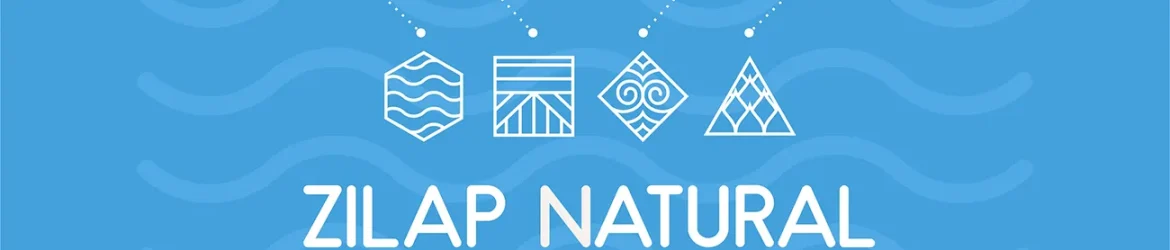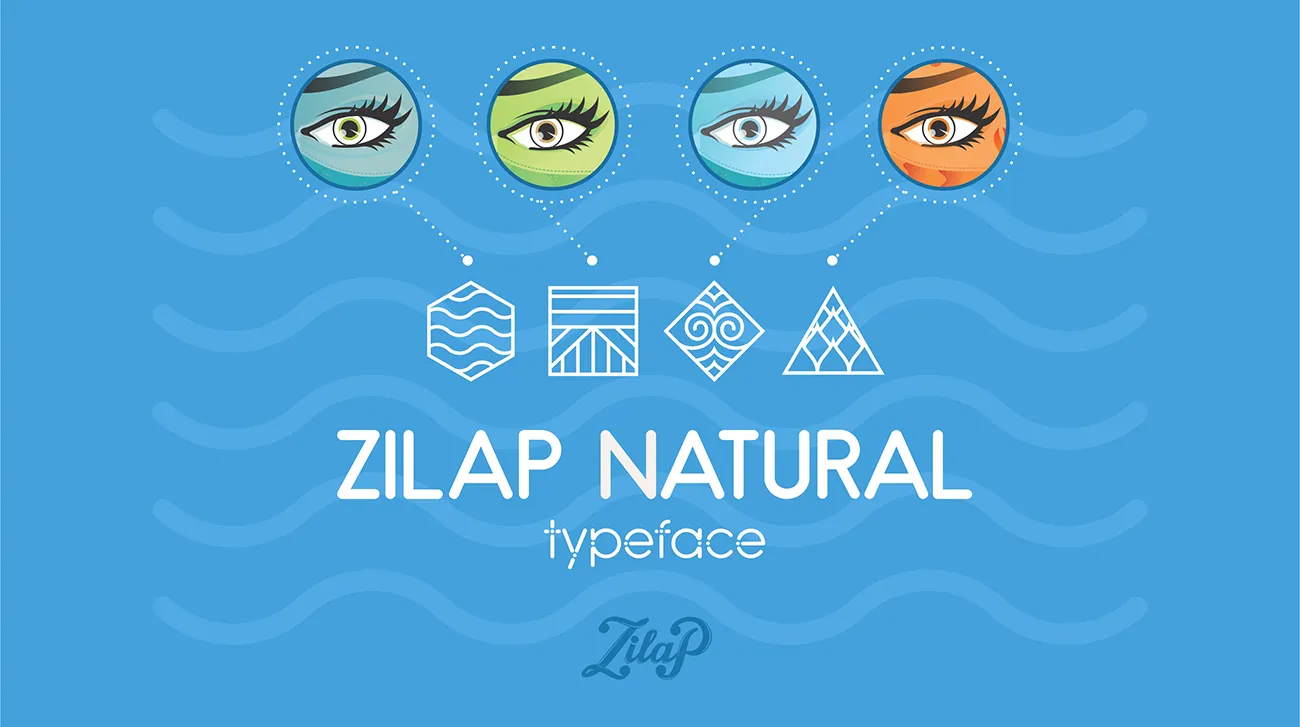
Zilap Natural Font
A Zilap Natural Font é uma elegante escolha para designers que buscam um estilo clean e moderno. Seu design suave e agradável aos olhos combina perfeitamente com diversos projetos, desde sites pessoais até portfolios de design gráfico. Esta fonte sans serif traz uma sensação natural e fluida à sua composição textual sem perder nenhuma destreza ou detalhe. Feita pelo designer lj.design, a Zilap Natural é uma ótima opção para aqueles que desejam um estilo moderno com um toque de serenidade. Suas linhas leves e retas criam um equilibrio entre simplicidade e sofisticação, tornando-a ideal para aplicativos digitais como blogs ou sites onde é importante ter uma aparência clean e profissional. Com Zilap Natural, sua fonte escolhida traz um toque de leveza à sua criação digital, permitindo que você atinga a perfeição no design do layout.